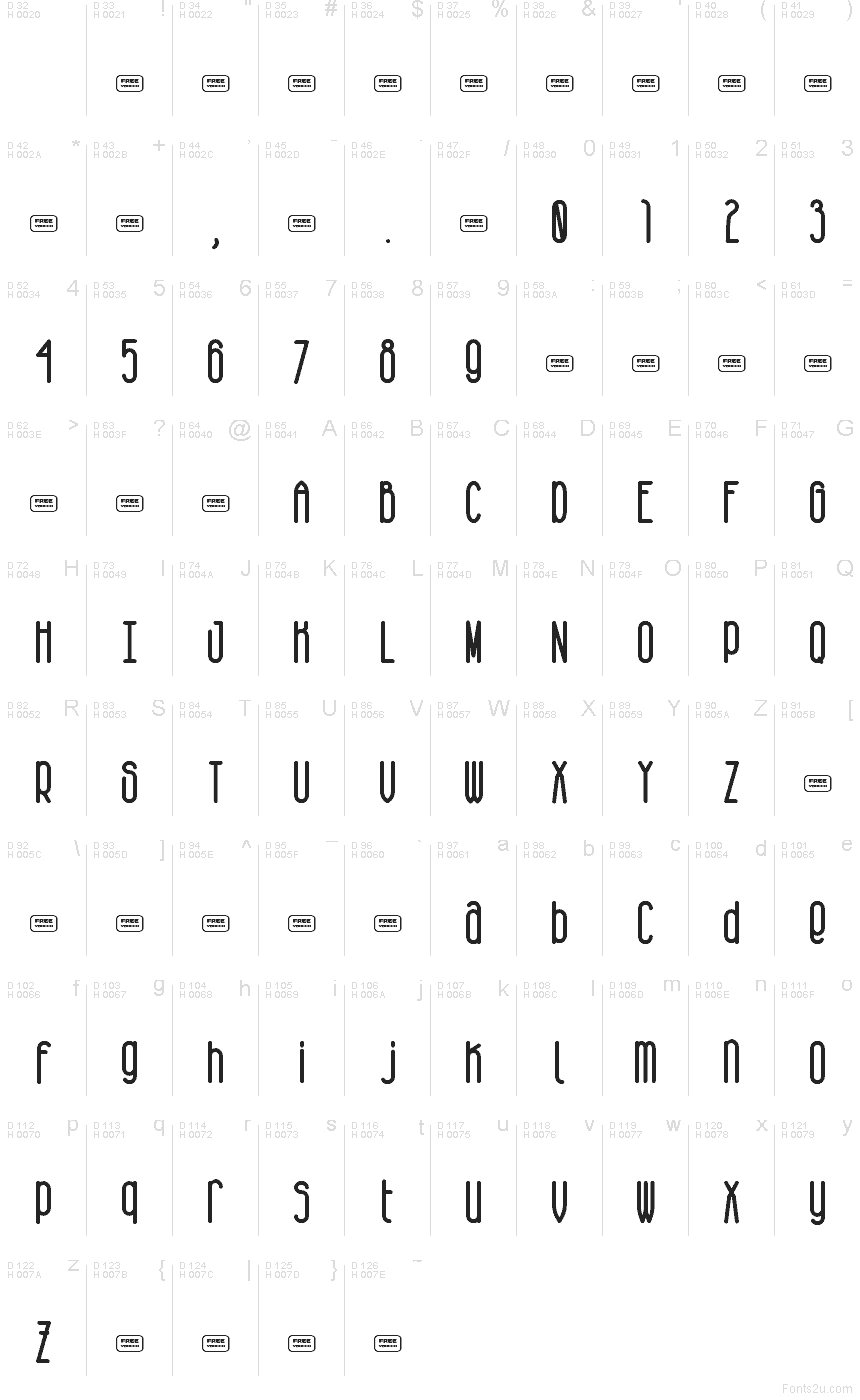
Lumilance Free Trial
تُعد Lumilance من Typefactory خط عرض مجاني بنمط ريترو، يتميز بضربات طويلة ومستديرة وإيقاع عمودي ضيق يذكرنا بلوحات المتاجر الكلاسيكية. الأشكال العمودية المتكررة تمنح النص قواماً انسيابياً ومتوازناً، بينما تمنع الزوايا الناعمة الخط من أن يبدو جامداً أو ميكانيكياً.
هذا المزيج يجعل الخط مثالياً للعناوين القصيرة على الملصقات، وأغلفة الألبومات، وهويات المقاهي البصرية، وتصاميم التغليف، والشعارات المستوحاة من واجهات المتاجر. كما أنه خيار ممتاز للشارات وتصاميم شبكات التواصل الاجتماعي، حيث توحي الحروف النحيفة والأنبوبية بأجواء النيون، والزجاج المرسوم، أو خطوط العرض التي سادت في منتصف القرن الماضي، دون الحاجة إلى أي زخارف إضافية.